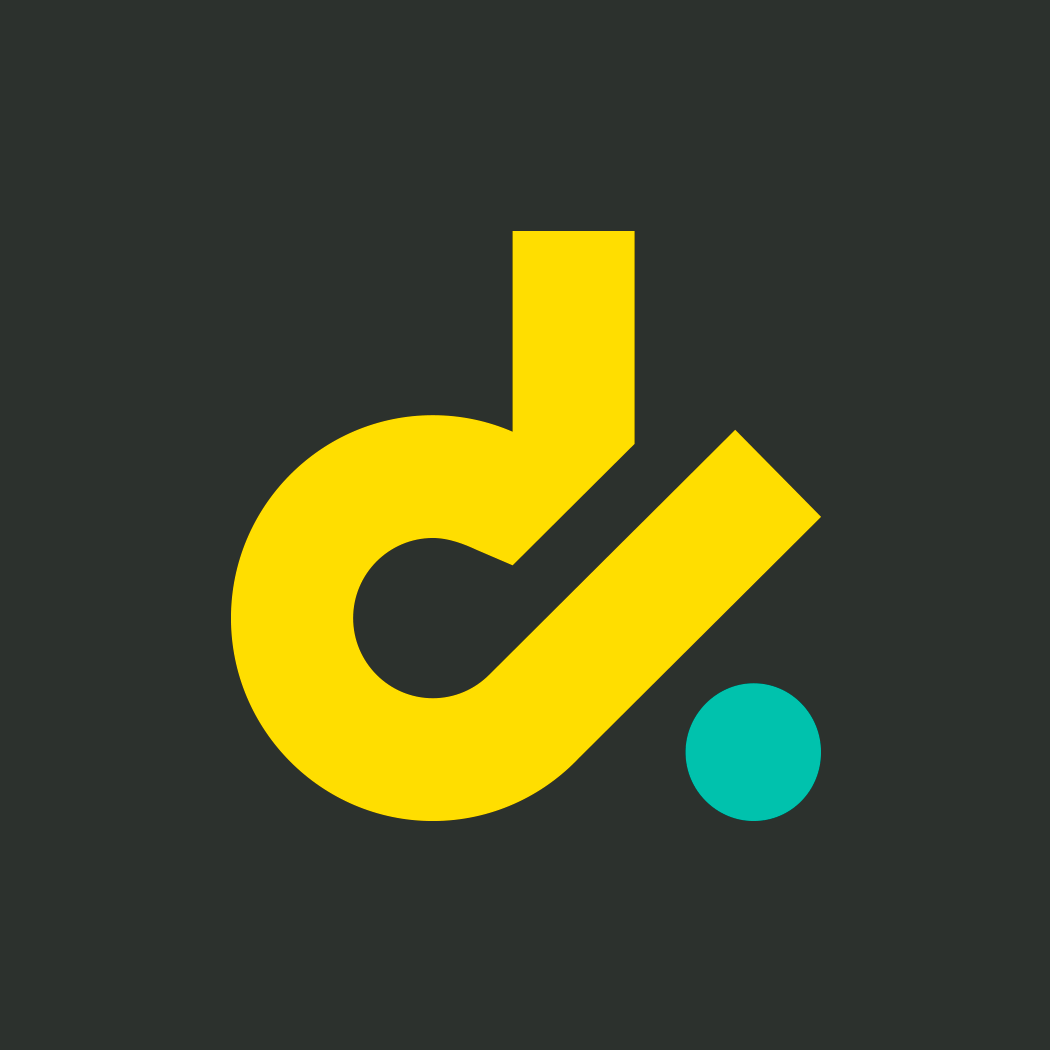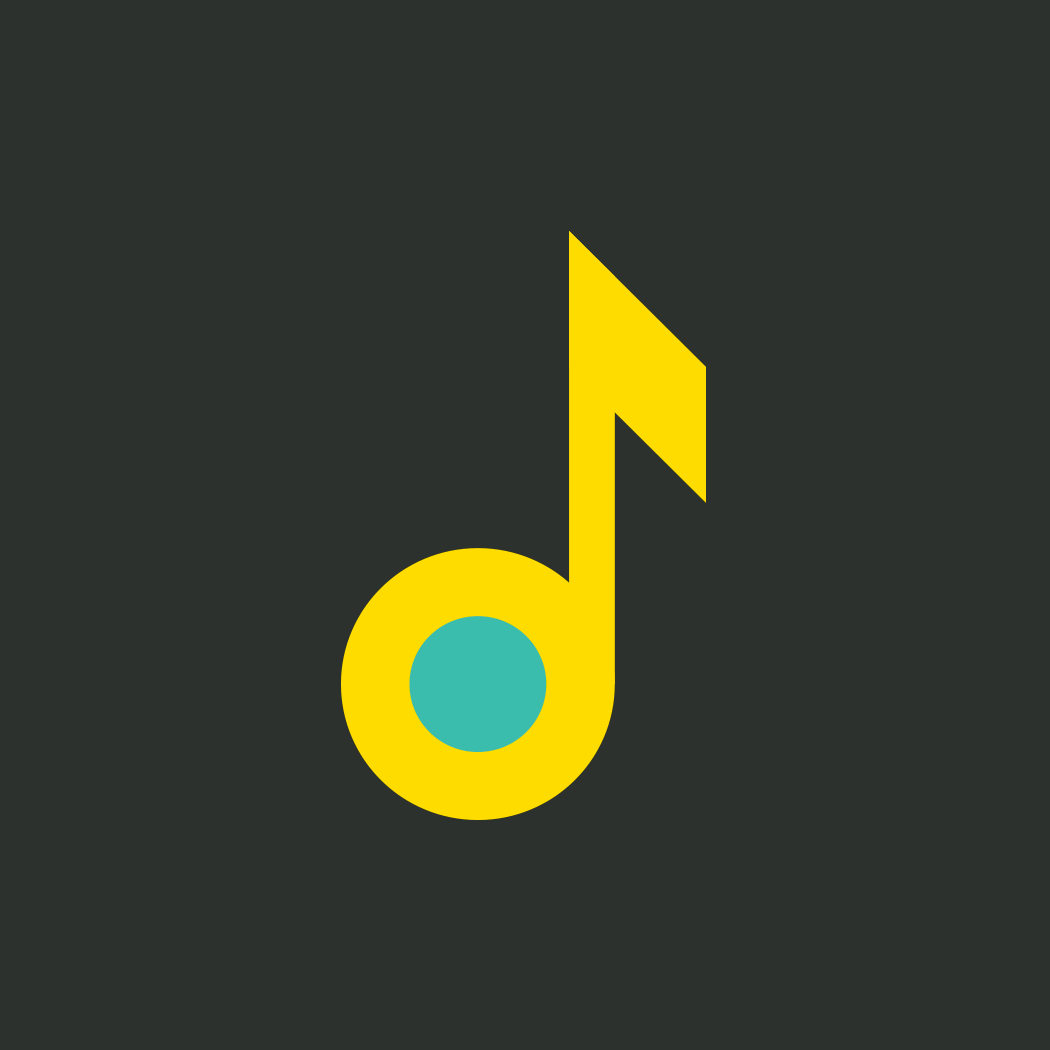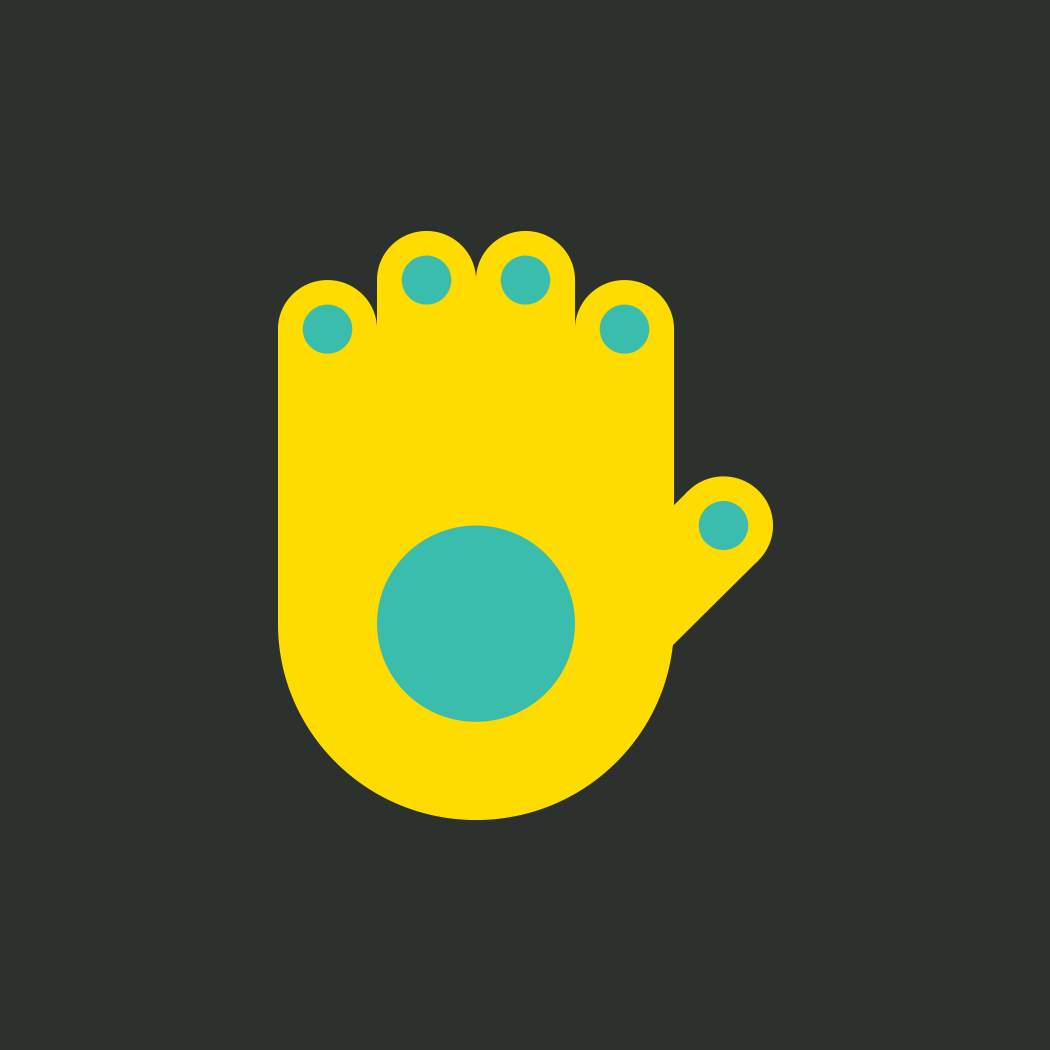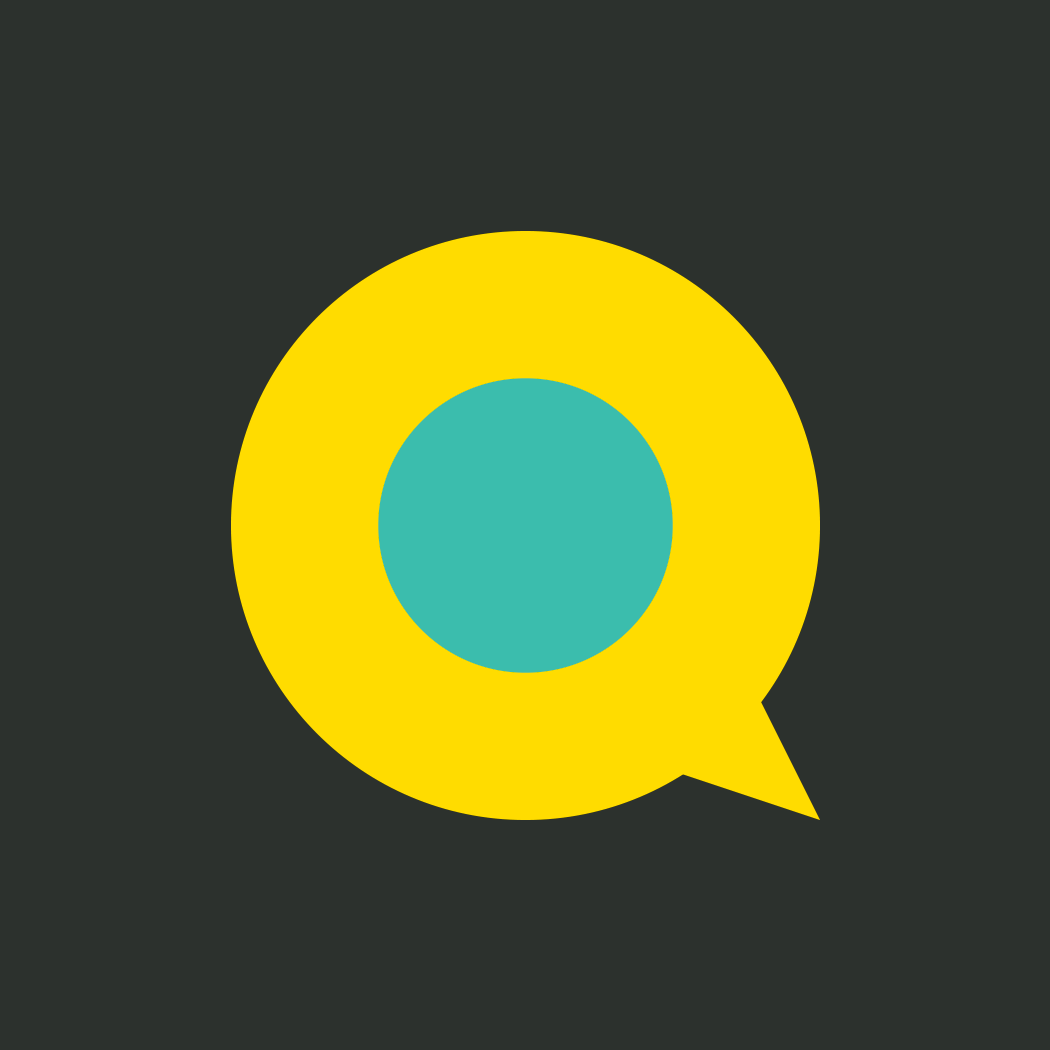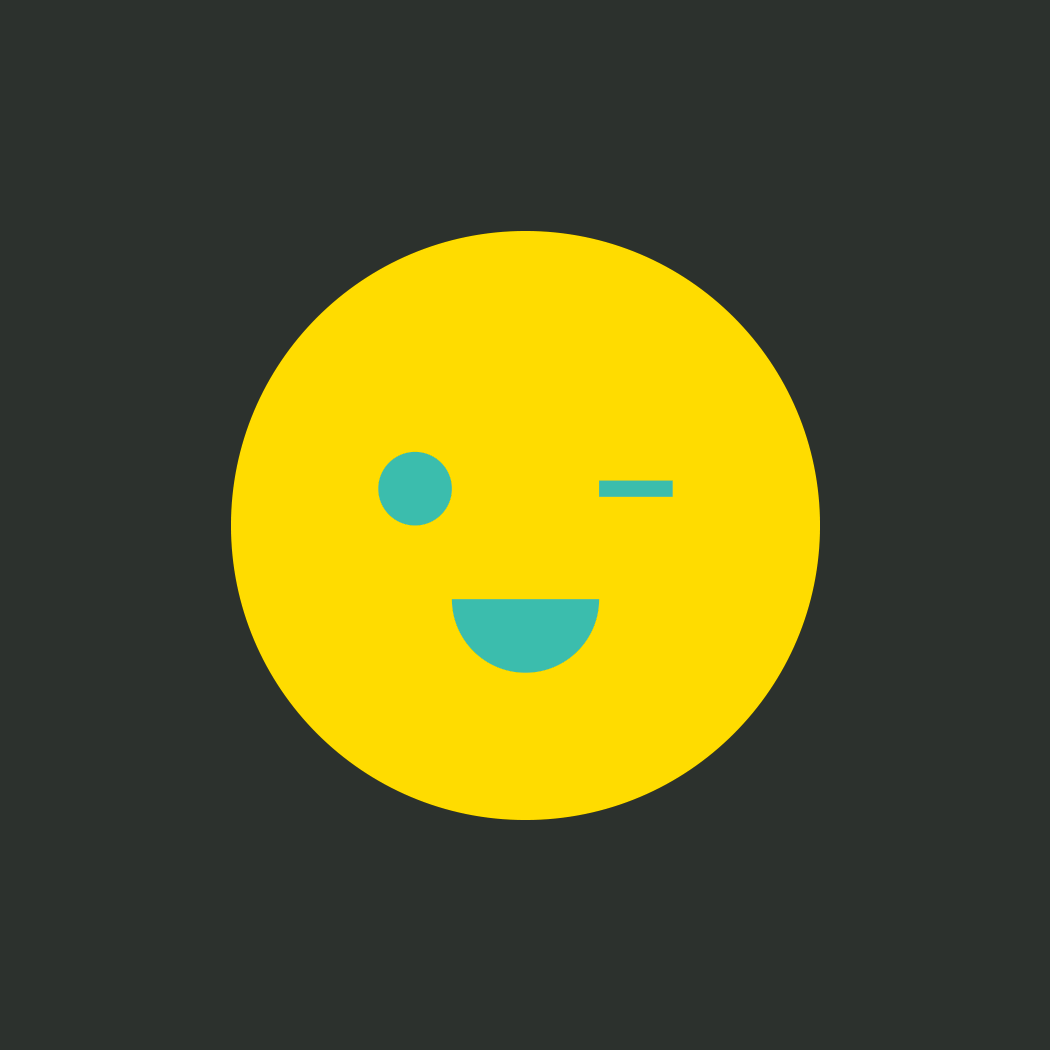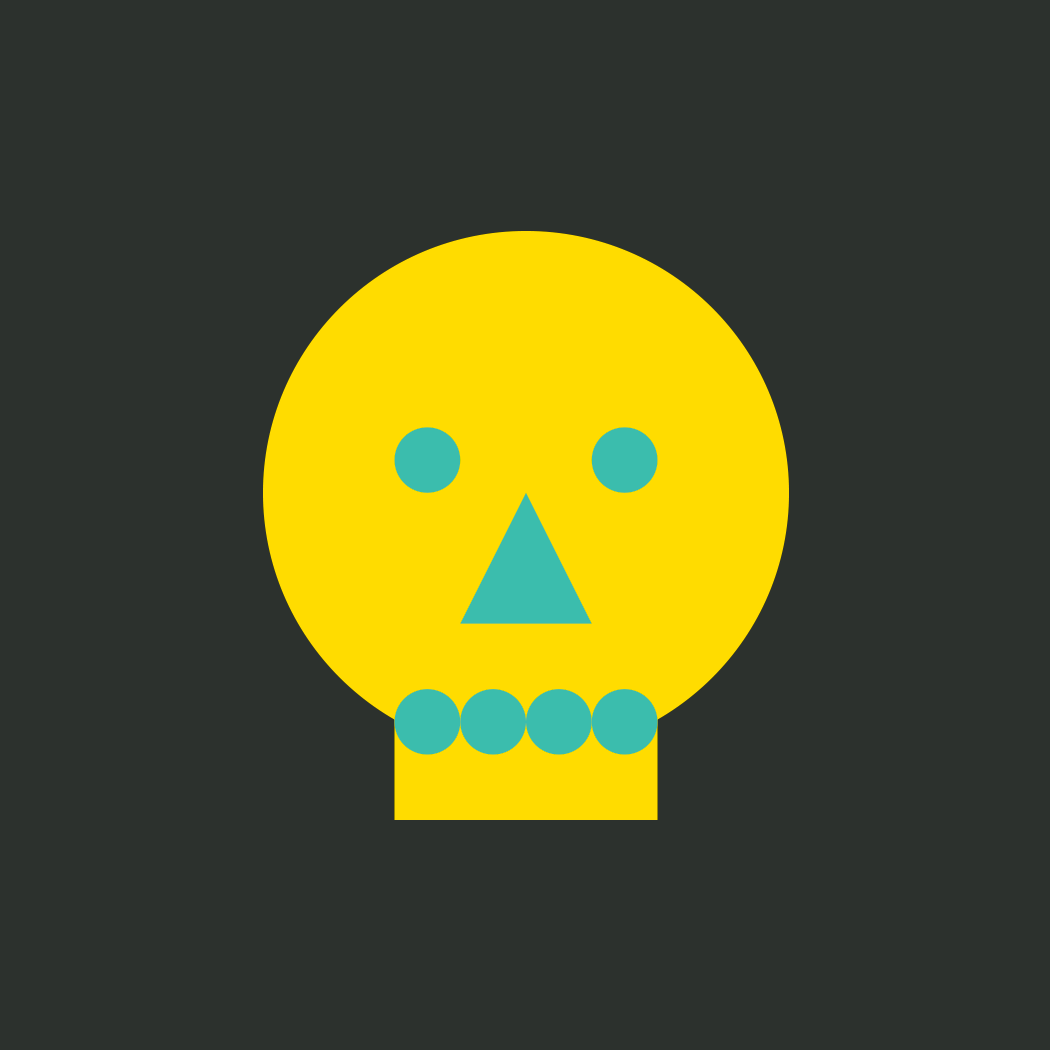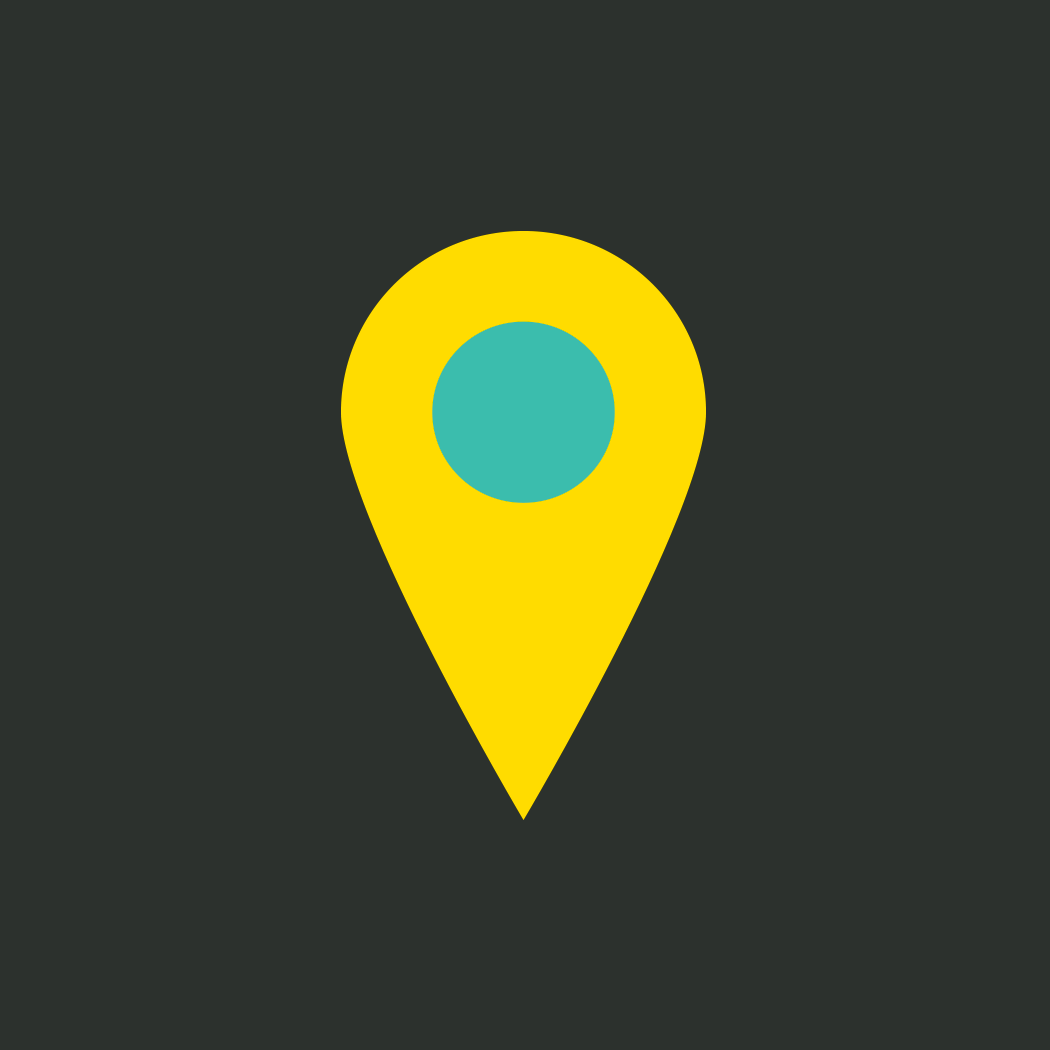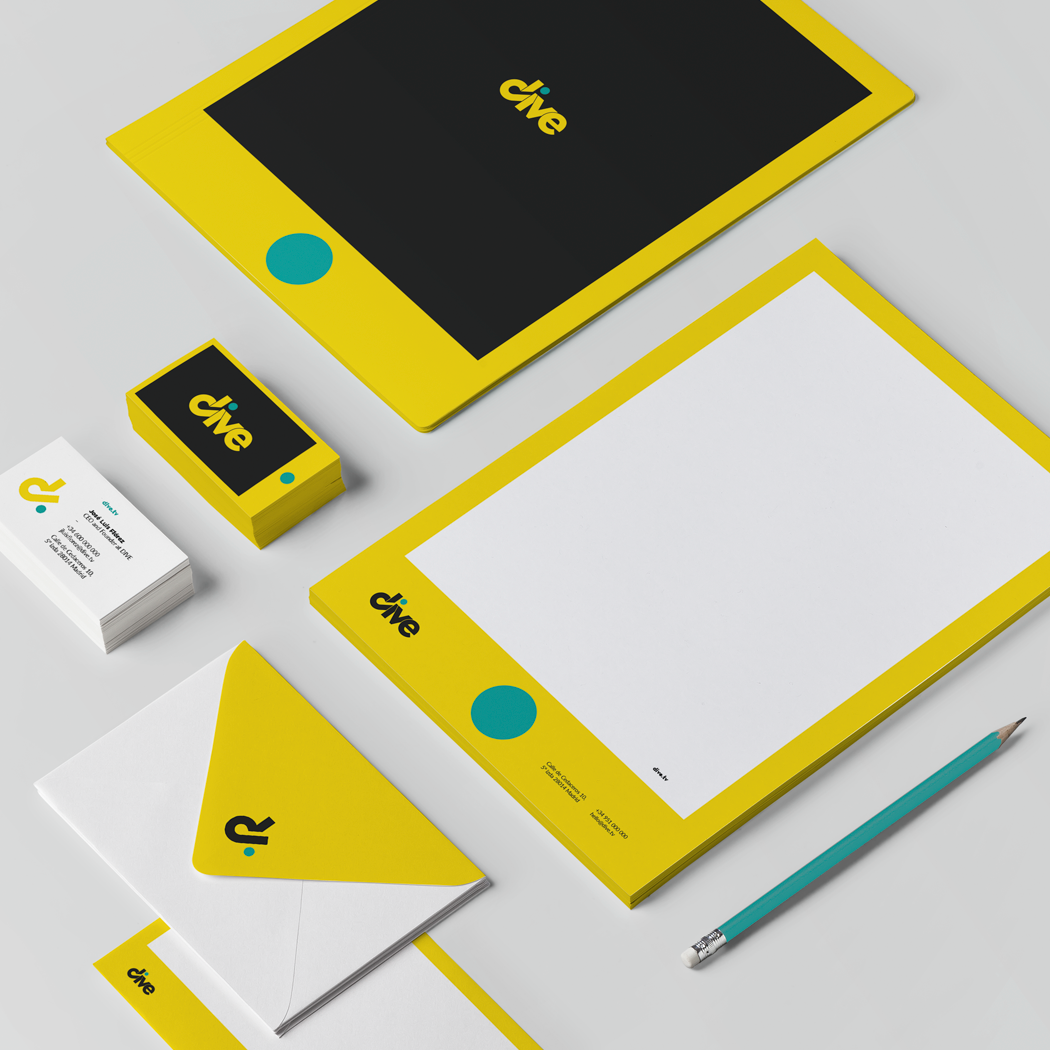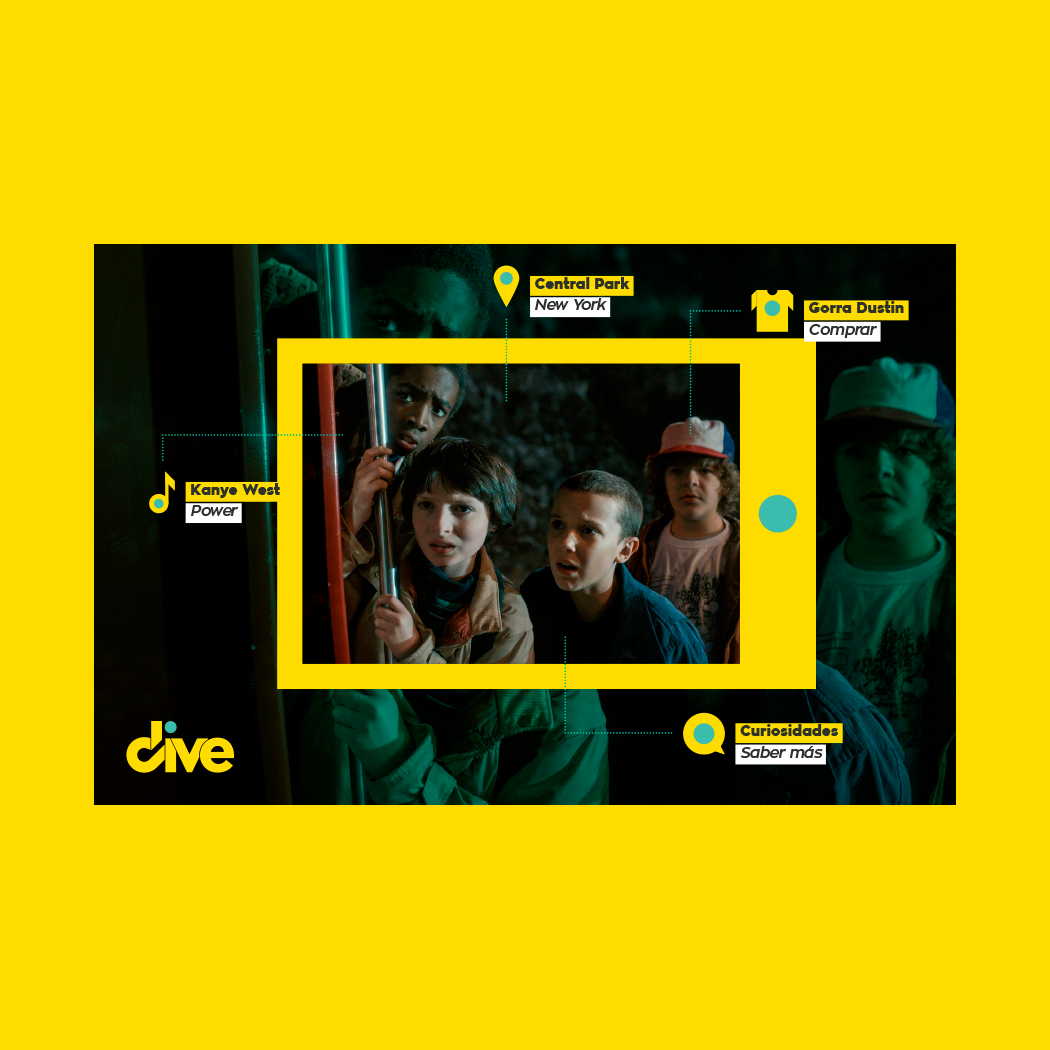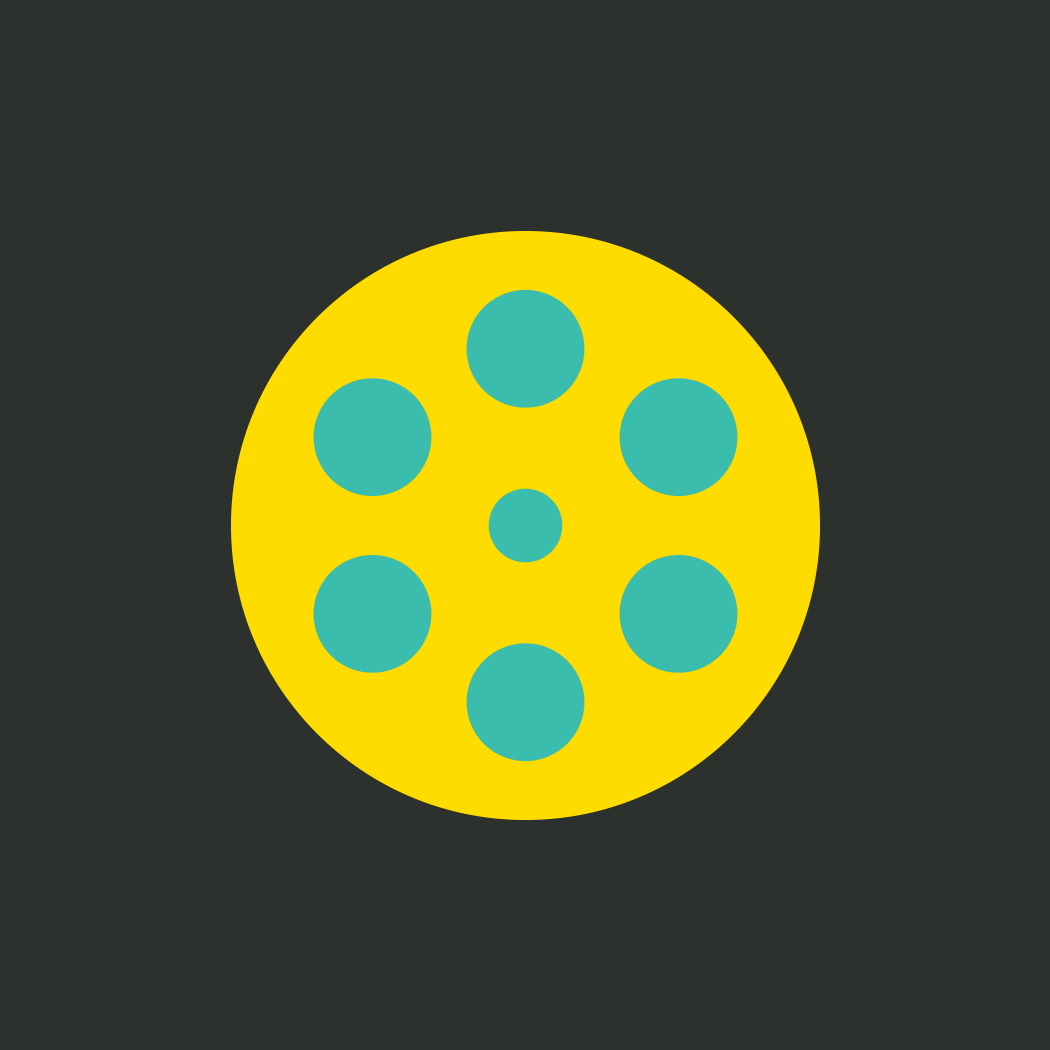
Sistema de iconos e identidad para dive. El punto verde del logotipo se tomó como referencia para convertirlo en el centro del desarrollo conceptual.
Identity and icon system for dive. The green point was the reference to develop a conceptual approach.